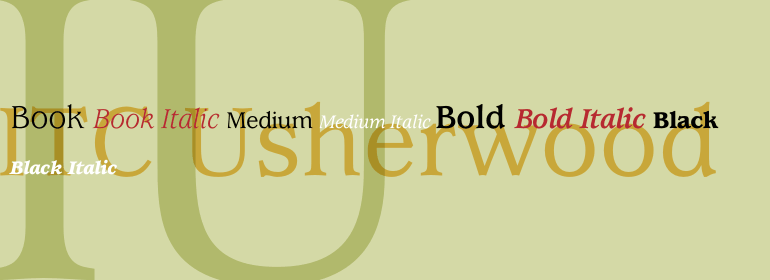
ITC Usherwood®
字体品牌: ITC(Monotype) 设计师:Usherwood,Leslie 字体分类:衬线体 字体属性:外文 字符集:Unicode 发布时间: 2018
ITC Usherwood字体由Leslie Usherwood设计,是一种介于传统与现代之间的非正式而又不失个性的字体。在这种字体中有Goudy, Bauer 以及 Augustea的痕迹,但ITC Usherwood既古典又现代,字形漂亮,设计实用。
ITC Usherwood font was designed by Leslie Usherwood, an informal and personablefont which bridges the gap between tradition and modernity. There are hints of Goudy, Bauer and Augustea in this font, but ITC Usherwood remains both classic and contemporary, beautiful in form and functional in design.